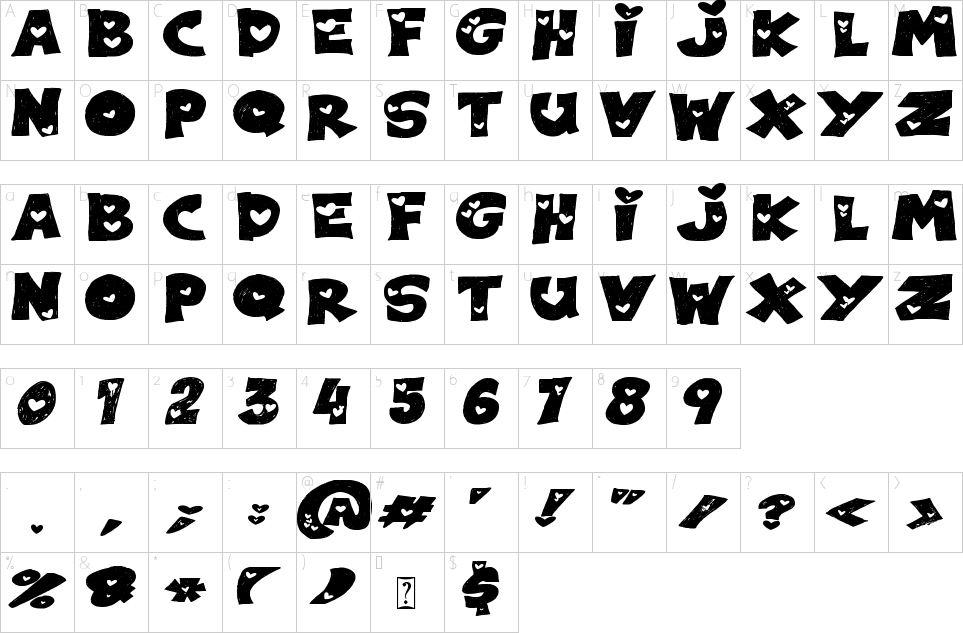
A fonte ‘Puppy Love Brush’ é uma opção elegante e amigável para designers gráficos, especialmente aqueles que desejam criar um tom delicado e suave em seus trabalhos. Desenvolvida pelo designer desconhecido, esta fonte vem em versões para Windows e Mac. Com seu toque suave e alegre, a Puppy Love Brush oferece um estilo que se adapta perfeitamente a designs de lojas de frutas, produtos infantis, ou qualquer outra criação que busque um ar alegre e carinhoso. Sua popularidade crescente é evidenciada pelo fato de que a fonte já foi baixada mais de 900 vezes. Se você está procurando por uma fonte que seja tanto usada quanto encantadora, a Puppy Love Brush pode ser uma opção perfeita para seu próximo projeto.